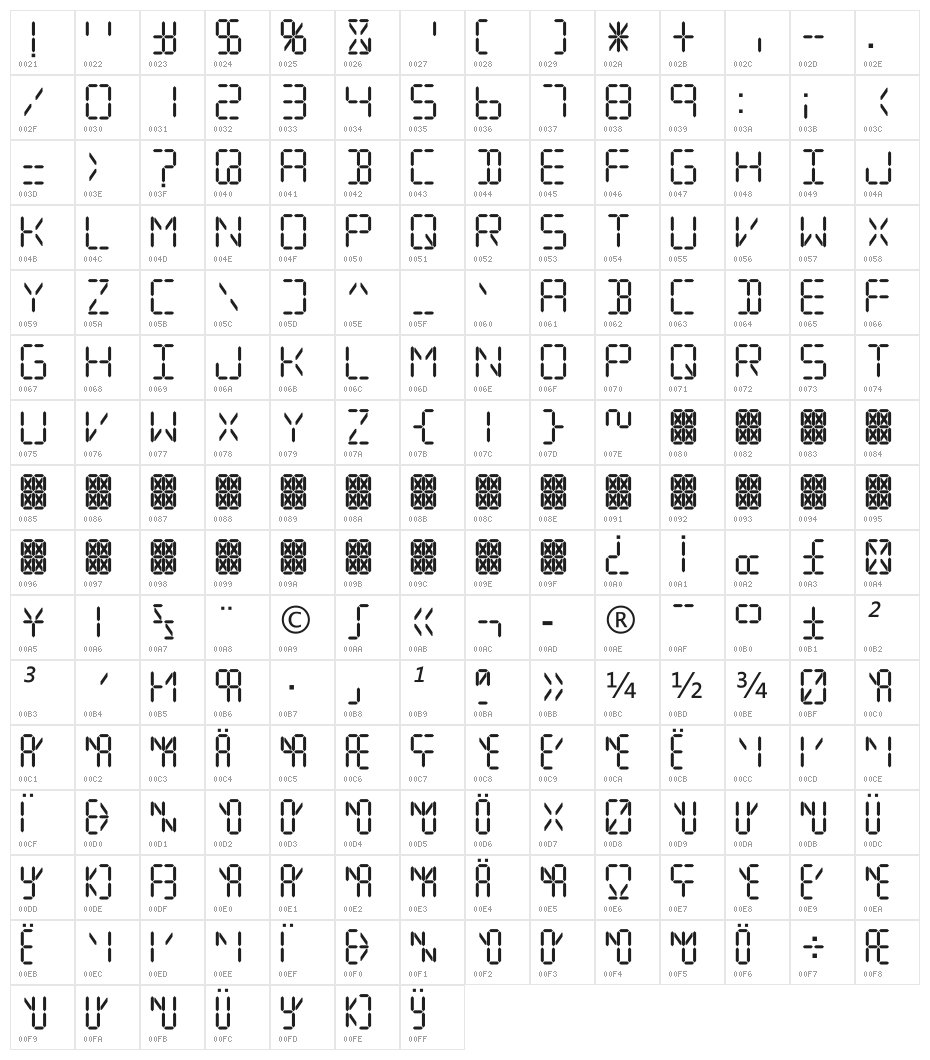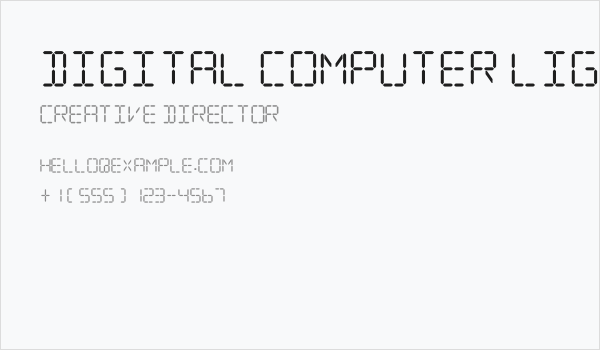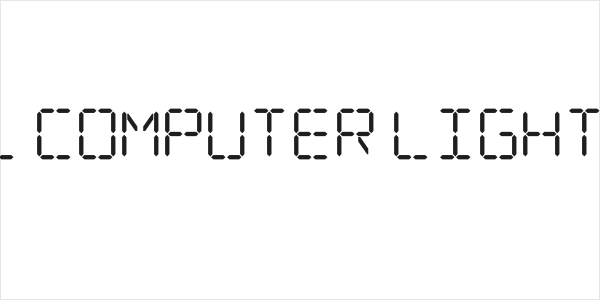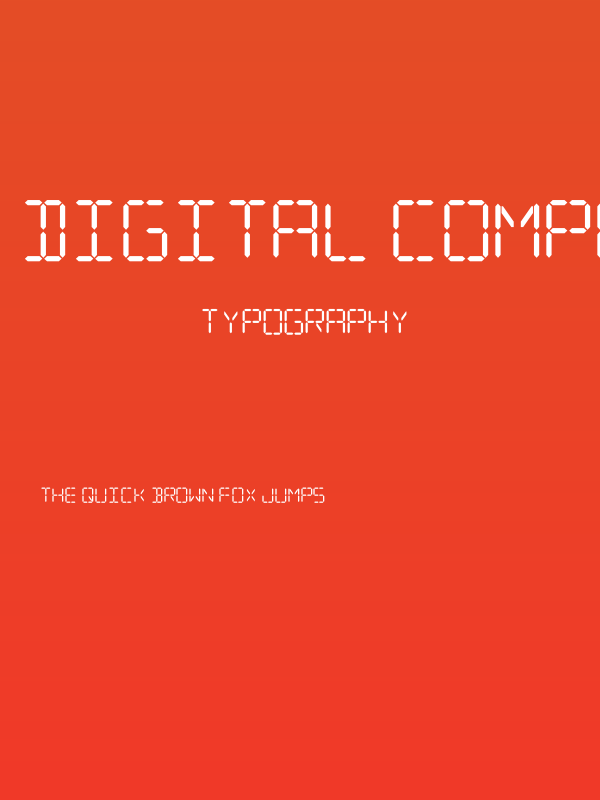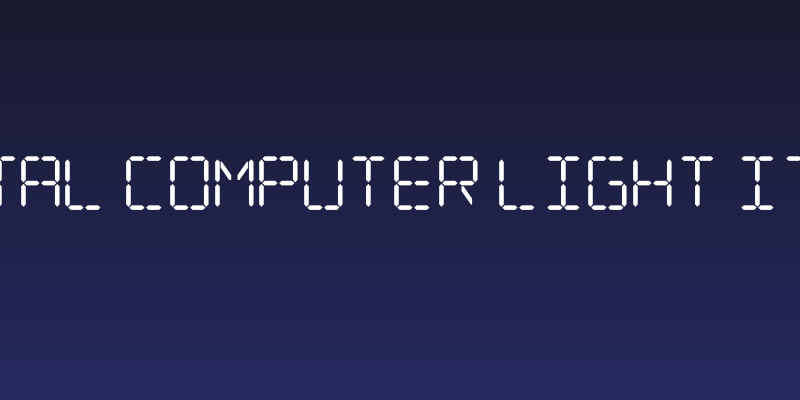
Digital Computer Light Italic Font
| حالة الاستخدام | Logos, Headlines, Digital displays |
| مشاريع مقترحة | Ideal for digital-themed designs, retro tech projects, electronic interfaces, and futuristic branding. |